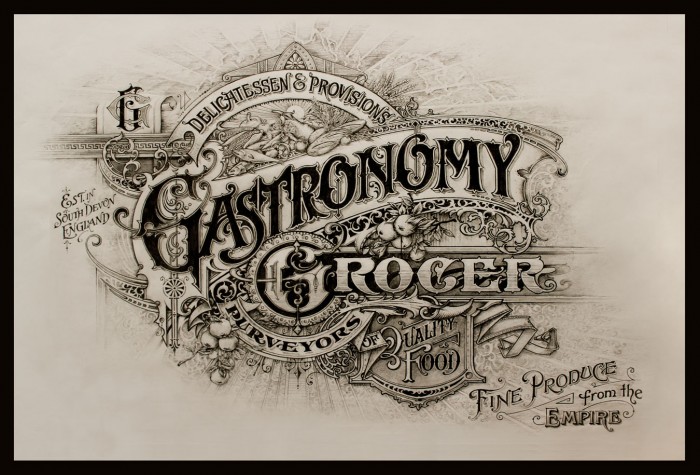
Typ / Kategorie / Klassifikation handgezeichneter Schrift
ich suche eine Schriftart, wie sie hier aussen und oben für die Texte "Est. in South Devon England", "Delicatessen & Provisions" und "Fine Produce from ehe Empire" verwendet wurde.
Wie nennt man diesen Typ Schrift und wo finde ich soetwas? Ich hab schon viel gesucht, aber ohne Anhaltspunkt ist das echt schwer!
Nun, nach der Schriftart wiorst du wohl dauerhaft suchen, da es sich eben nicht um eine Satzschrift, sondern um individuell gestaltetes Lettering handelt, in einem Stil, der so in etwa in der Zeit um 1880-1900 sehr verbreitet war.
Auch gibt es das noch heute, eine schöne Kollektion z.B. findest du auf der Website von Tobias Saul: